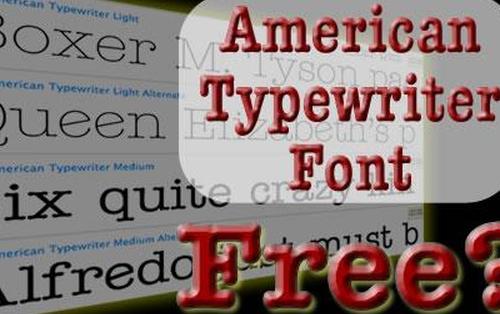
Шрифт American Typewriter используется в различных местах и способами. Его можно использовать в бизнес-проектах, дерзком дизайне и там, где уместен ностальгический вид.
История американского шрифта для пишущих машинок
Шрифт American Typewriter был создан в 1974 году дизайнерами Джоэлом Каденом и Тони Стэном для International Typeface Corporation. Он был основан на форме букв первых пишущих машинок, запатентованной в 1868 году.
Создание шрифта было в большей степени художественным занятием, чем может показаться; часть очарования пишущей машинки заключалась в небольших колебаниях давления чернил, в том, как шарик ударялся о бумагу, даже в оттенках или возрасте ленты пишущей машинки. У компьютера нет этих вариаций — каждая буква, каждое слово на экране или на печатной странице по умолчанию были бы одинаковыми.
Шрифт очень похож на оригинальный шрифт пишущей машинки, за некоторыми исключениями, такими как R, e, & и знак $. Шрифт был разработан таким образом, чтобы каждая буква занимала одинаковое количество места, что также известно как «моноширинный» шрифт.
Стэн и Каден работали над тем, чтобы сохранить ностальгию по процессу механической печати и в то же время сделать его достаточно ясным и профессиональным, чтобы соответствовать чистой резкости цифровой эпохи. Результатом стал шрифт American Typewriter, который до сих пор пользуется большим успехом.
Использование шрифта американской пишущей машинки